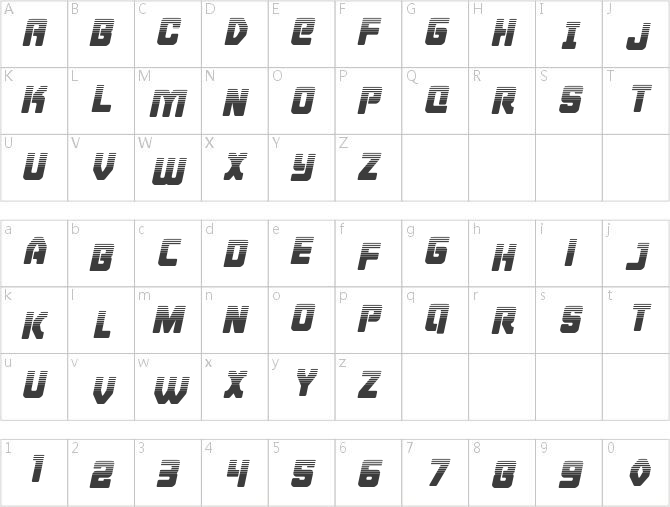
cyborgroosterhalfital 詳情頁
cyborgroosterhalfital字體字庫是一款讓人賞心悅目、百看不厭的英文字體,適合各類廣告和產(chǎn)品包裝設(shè)計(jì)應(yīng)用,字體大小0.07MB,格式為ttf字體,上傳用戶是錦程正陽,作者/版權(quán)方為未知